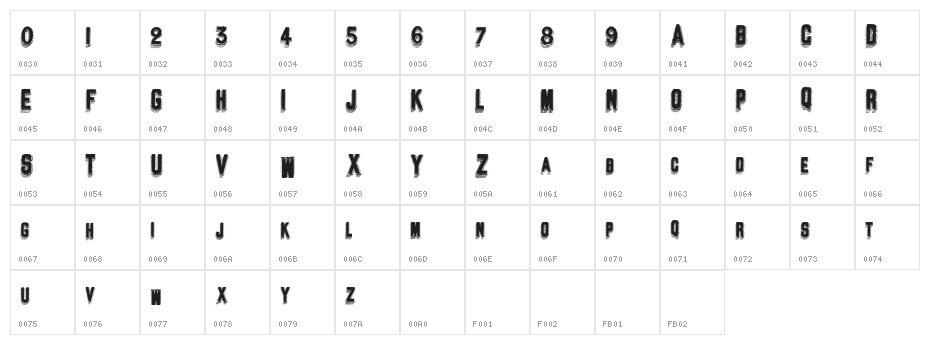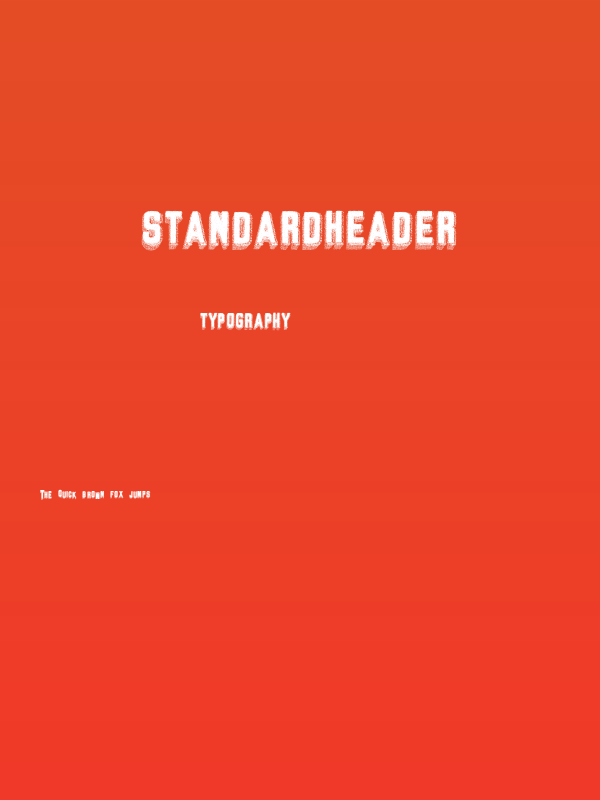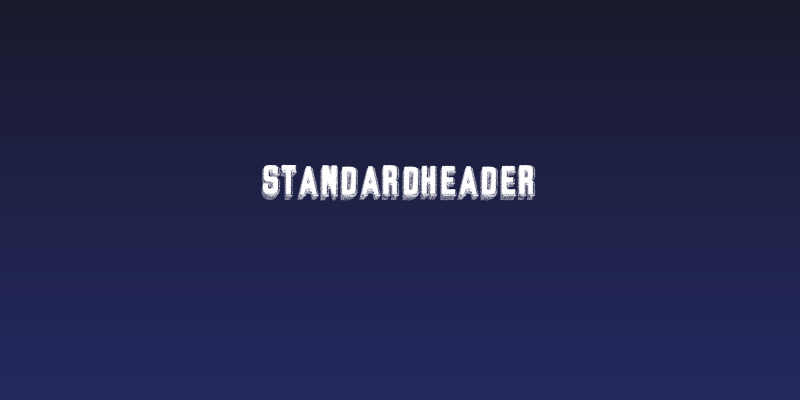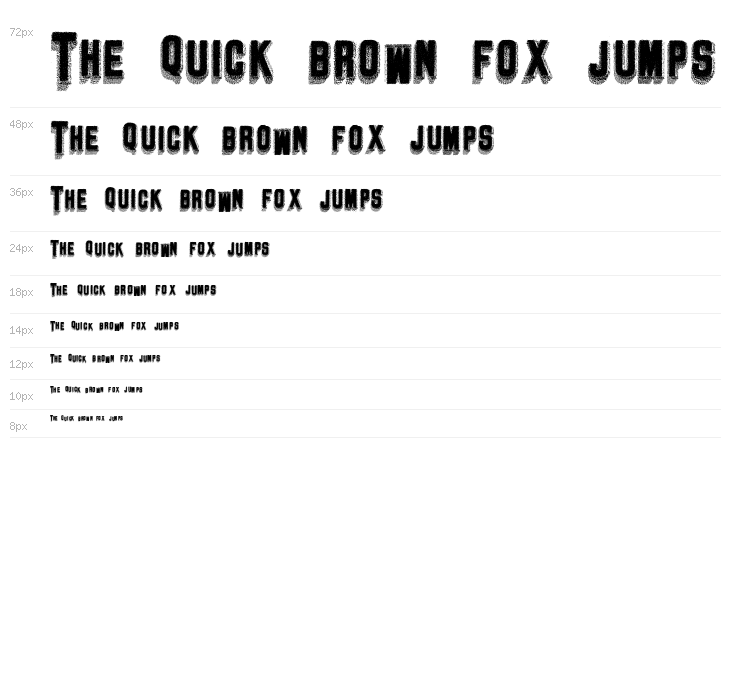
StandardHeader Font
✎ Distorted Eroded
| Categorie | Distorted Eroded |
| Progetti proposti | Ideal for posters, album covers, branding for edgy or vintage-themed products, and any design needing a bold statement. |